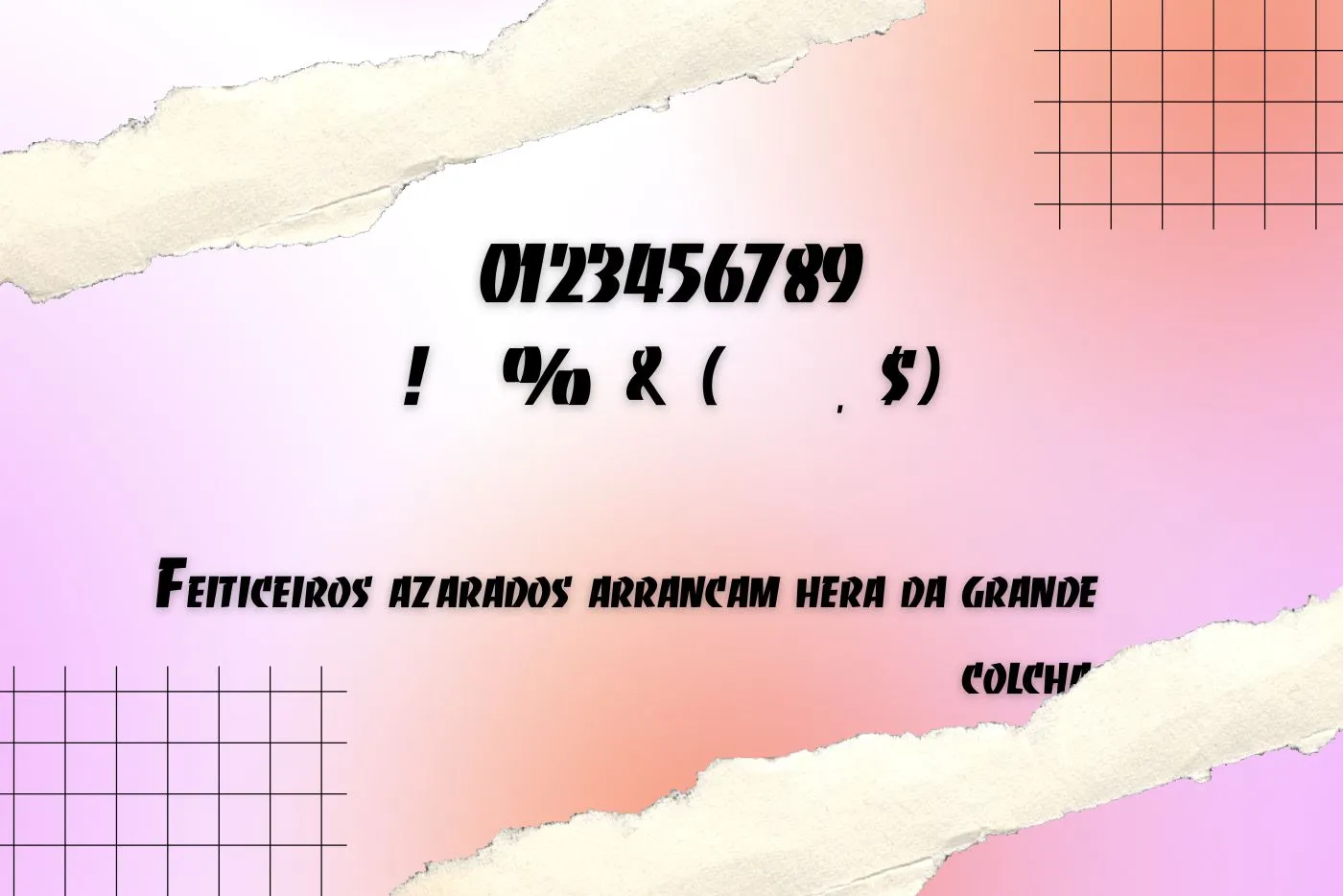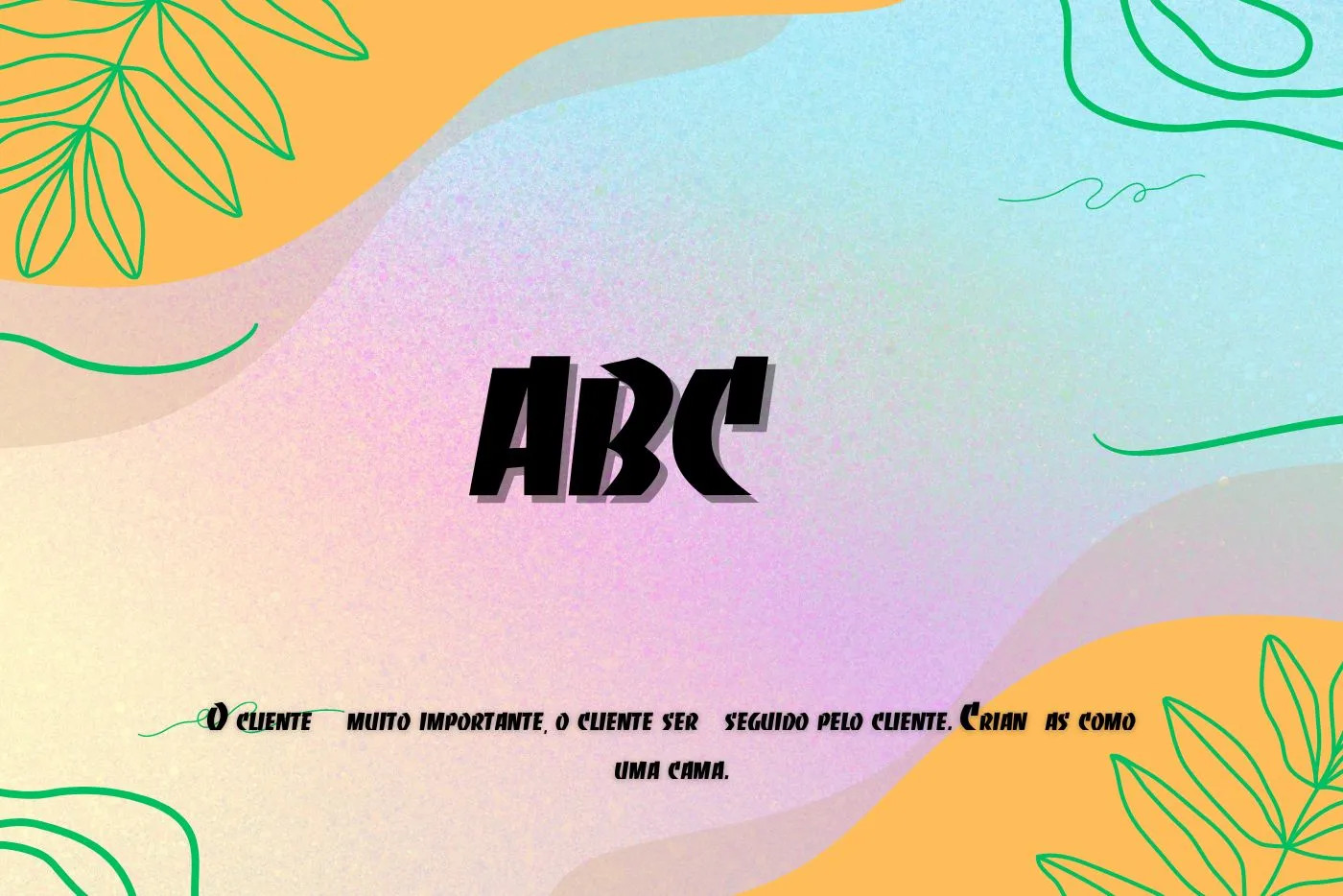
A fonte Thrasher é uma fonte ousada e impactante que carrega consigo um estilo de design inspirado no mundo do skate e da cultura urbana. Com seu design volumoso e letras angulares, essa fonte transmite uma sensação de energia e rebeldia.
O estilo distinto o torna perfeito para projetos que buscam um visual moderno e moderno. Além de seu apelo estético, é conhecido por sua legibilidade. Suas letras maiúsculas bem espaçadas e traços definidos permitem uma leitura clara, mesmo em tamanhos menores.
Com ela, você pode transmitir uma atitude arrojada e cheia de personalidade em seus projetos. Seja criando uma marca forte, um design marcante ou adicionando um toque ousado e urbano a qualquer projeto, essa fonte é uma escolha popular para quem quer se destacar com estilo.
Visualização da Fonte Thrasher
Família de Fontes Thrasher
- Thrasher Bold
Visão Geral da Revista de Fontes Thrasher
É uma revista icônica e influente na cultura do skate, oferecendo conteúdo autêntico e relevante desde sua fundação em 1981. Conhecida por suas histórias de alta qualidade, fotos e vídeos incríveis, a revista captura a essência do skate e transmite uma atitude apaixonada e rebelde ao esporte. .
Além da revista, a marca Thrasher expandiu seu alcance por meio de produtos e colaborações, tornando-se um ícone reconhecido mundialmente. É uma instituição no mundo do skate, inspirando skatistas e contribuindo para o crescimento da cultura do skate.
Maneiras em Que a Fonte Thrasher Pode Ser Usada
Thrasher Font é uma fonte notável, devido à sua ampla gama de glifos e estilos excepcionais. Este tipo de letra é usado por designers para aumentar a beleza dos projetos. Você pode usar essa fonte para edição de vídeo e edição de fotos. Esse tipo de letra pode ser usado para criar designs personalizados na parte de trás da capa do seu celular e em muitos outros gadgets.
Ele fornece uma aparência nova que permite usá-lo para criar logotipos e identidades visuais para marcas de tendências. Além disso, seu visual chamativo ajuda a ser usado em campanhas publicitárias.Este tipo de letra pode ser usado para criar cartões de casamento, felicitações e convites e irá realçar o brilho de tais cartões. Se você está organizando qualquer evento em sua casa, pode adicionar um toque de brilho à sua casa com este tipo de letra incrível. Você pode emparelhá-lo com a fonte Hestina.
Esta fonte encantadora pode ser usada para escrever suas citações ou linhas favoritas. Devido ao seu recurso visualmente atraente, você pode usá-lo para criar layouts de sites, revistas, capas de livros ou qualquer outro tipo de material impresso. Você pode usá-lo para criar seu currículo, tarefas, documentos, apresentações e muitos outros projetos. Emparelhar esta fonte com a Berkshire Swash Font dará um resultado impressionante aos seus designs.
Algumas Características da Fonte Thrasher
A fonte Thrasher tem várias características distintivas que a tornam facilmente reconhecível e associada à cultura do skate. Tem um estilo grunge envelhecido com letras irregulares, texturas ásperas e linhas que parecem ter sido pintadas ou rabiscadas.
As letras são angulares e inclinadas, transmitindo uma sensação de movimento e energia. As letras nele são generosamente espaçadas, o que aumenta a legibilidade e a visibilidade das palavras ou frases escritas com ele.
Que tipo de fonte é a fonte Thrasher?
É um tipo de letra decorativo que surgiu há muitos anos e ganhou elogios depois de ser usado no logotipo de uma revista popular e líder, ‘Thrasher’, que destaca diferentes pontos, incluindo música, skate, etc.
Vale a pena usar a fonte Thrasher?
Thrasher Font é uma das fontes mais usadas. Muitos designers aplicaram esse tipo de letra com o par de fontes Muller em seus projetos de design em todos esses anos. Tem uma aparência cativante que faz com que o design valha a pena ser apreciado. Portanto, você sempre pode optar por esse tipo de letra para seus projetos.
Onde a fonte Thrasher pode ser usada?
Você pode usar a fonte em vários lugares e, acima de tudo, seria melhor para logotipos. Fora isso, use a fonte em capas, imagens, sites, anúncios, layouts, banners, designs, textos, projetos impressos e digitais e muitos outros lugares.